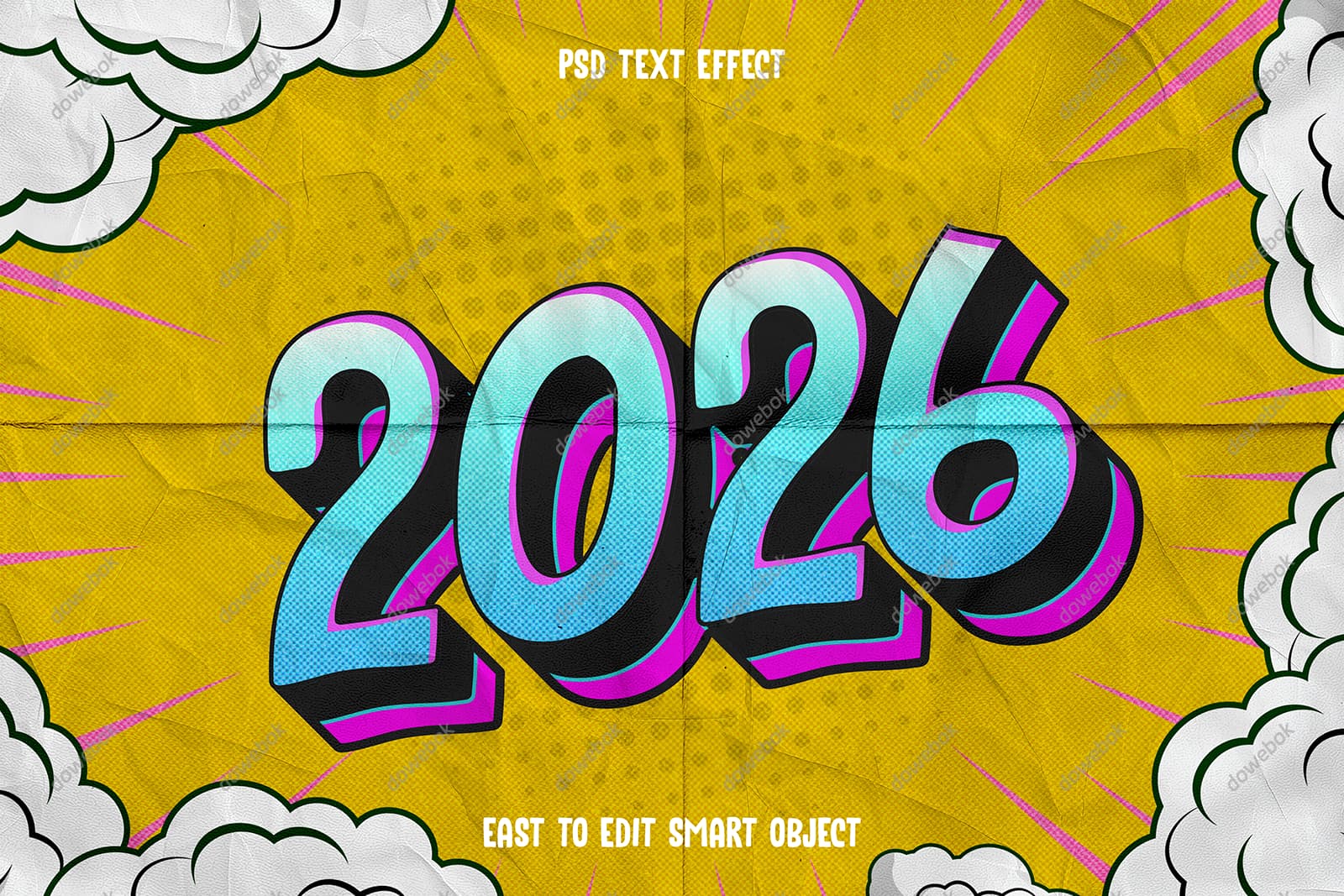
这是一款由立体涂鸦数字设计的 2026 新年快乐背景素材,明黄褶皱背景配粉红射线,“2026” 以蓝紫渐变的立体波普字体呈现,边缘醒目且富有漫画质感,四角缀着卡通云朵,上下标注 “PSD TEXT EFFECT”“EASY TO EDIT SMART OBJECT”。整体风格活泼跳脱,波普元素与撞色设计结合,既显潮流创意,又突出字体效果的可编辑属性,适配年轻向海报、创意物料等场景。